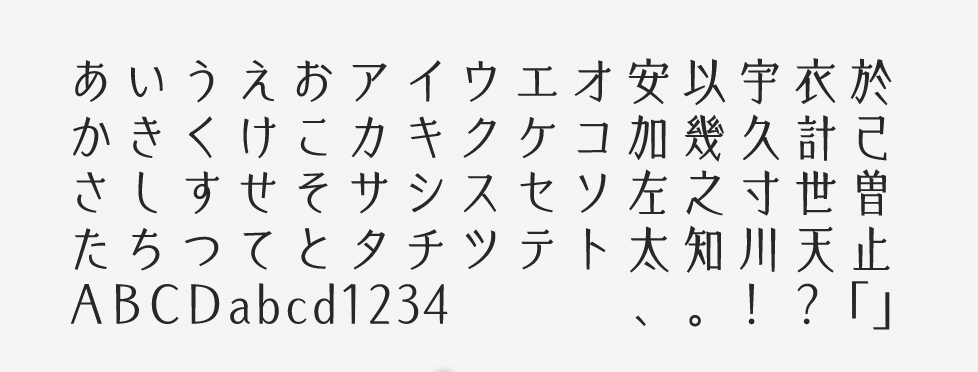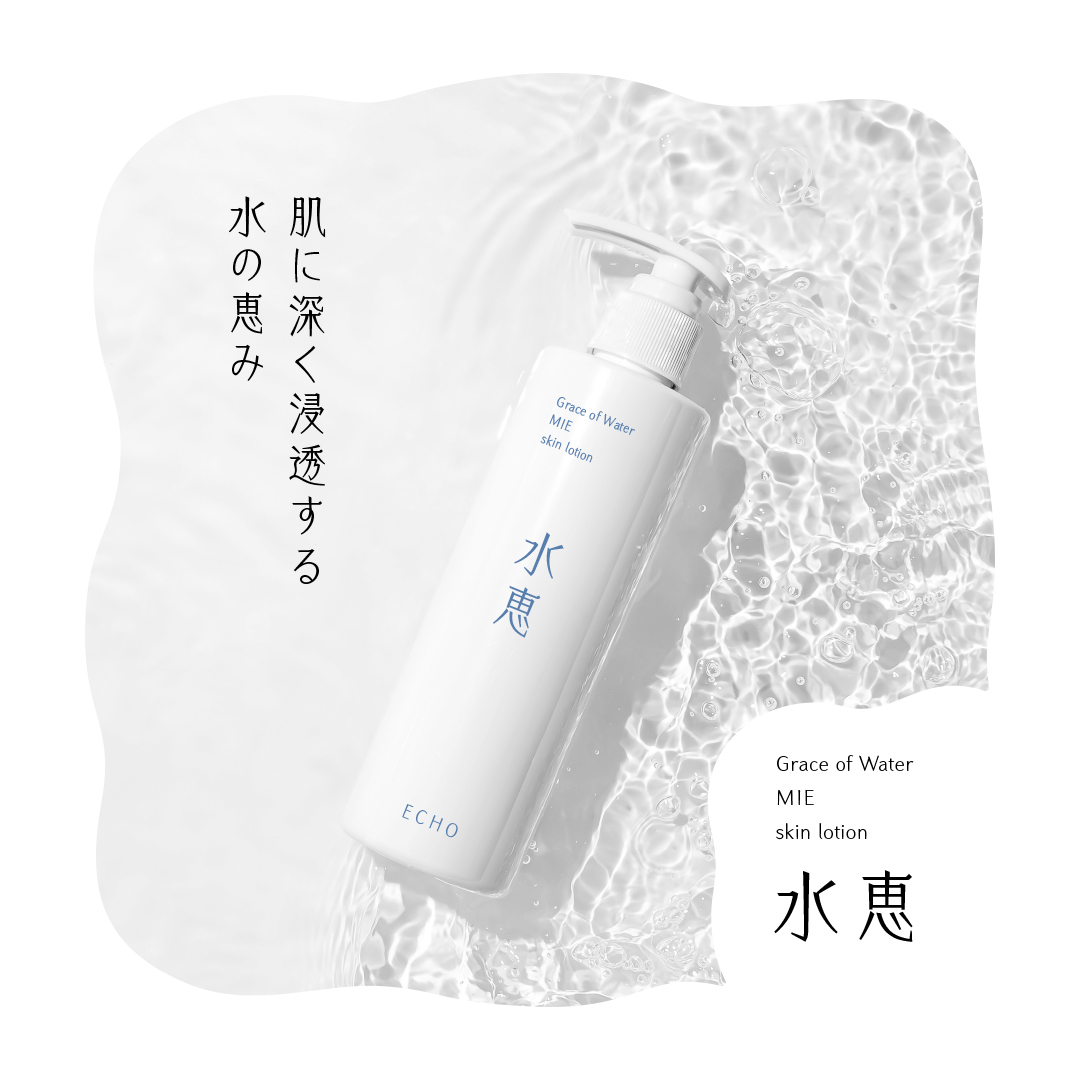
「エコー」について
エコーは2018年に提供が開始された書体で、L・R・Bの3ウエイトで構成されています。重心が高く、直線的なデザインのフォントです。全角に対して骨格が狭めに設計されており、長体のような縦長のプロポーションに見えます。縦長の形は上品さなどのイメージにつながり、美容関係のような清潔感の表現が求められるジャンルにも最適です。
「エコー」の特徴
全角の幅に対して縦長であるエコーでは、それぞれの文字の左右に広めの余白が生じています。そのため、デフォルトで横方向にベタ組みすると、まるでアケ組みしたようなゆったりとした空間での文字送りが可能です。
OpenTypeフォント機能のプロポーショナルメトリクスを有効にすると、それぞれの字幅に合わせた文字送りとなり、デフォルトの状態とは表情が異なる緊張感を演出できます。このとき、長体幅は全角に対して約86%相当です。
作例は化粧品のラベルのデザインなので、清潔感のイメージを表現できるエコーを採用しました。その特性上、文字列を縦に組むと1行の幅は細長くなり、すっきりとした美しいラインが生み出されます。まさにイメージにぴったりなフォントだと思いながら選びました。
雑誌、パンフレット、商品パッケージ、ロゴ、ラベル